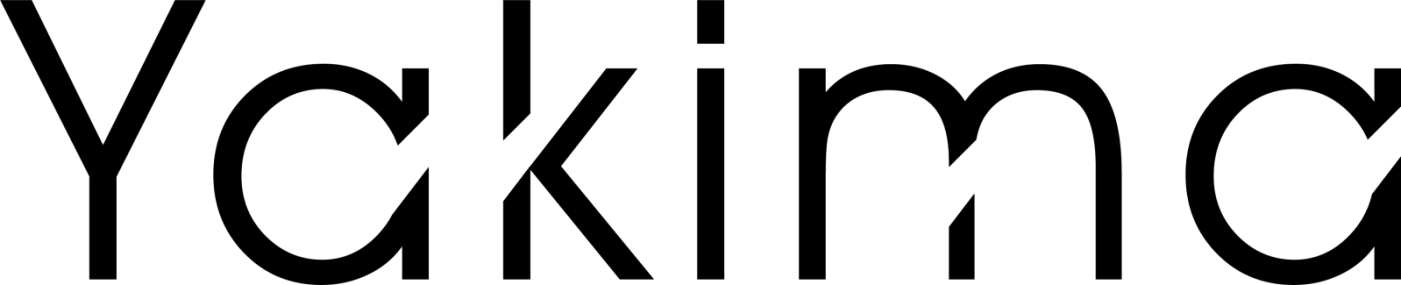
Welche Schrift könnte das wohl mal wieder sein?
Ich habe da eine Schrift, die es so wahrscheinlich gar nicht gibt, da sie nachträglich bearbeitet wurde. Aber welche Schrift käme der wohl am nächsten? Oder gibt es die gar so?
Sieht einer Futura mit frisierten Oberlängen ähnlich, über die diverse weiße Streifen gelegt und dann ausgeschnitten wurden.
Stimmt, Du bist dichter dran als ich – da müsste man dann fast nur noch die weißen Streifen rausschneiden. Die Punzen im a sind nicht ganz rund und der obere rechte Arm vom k hat eine leicht andere Neigung. :nicken:
Die Century Gothic wäre eine (kostenlose) Alternative. Soweit ich mich erinnern kann, gab es die als System-Schrift bei Windows XP dazu.